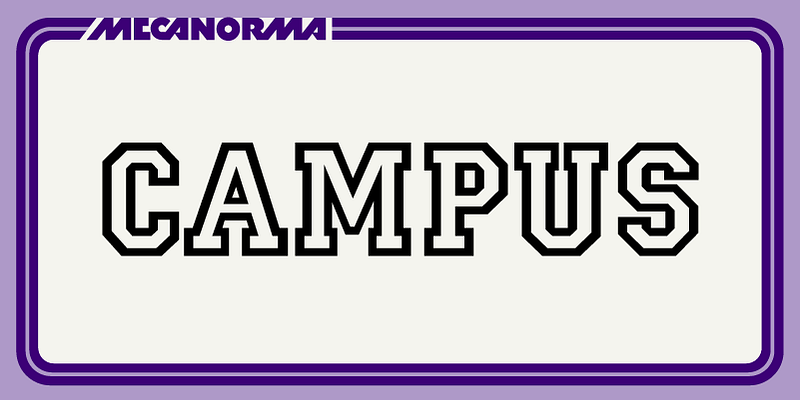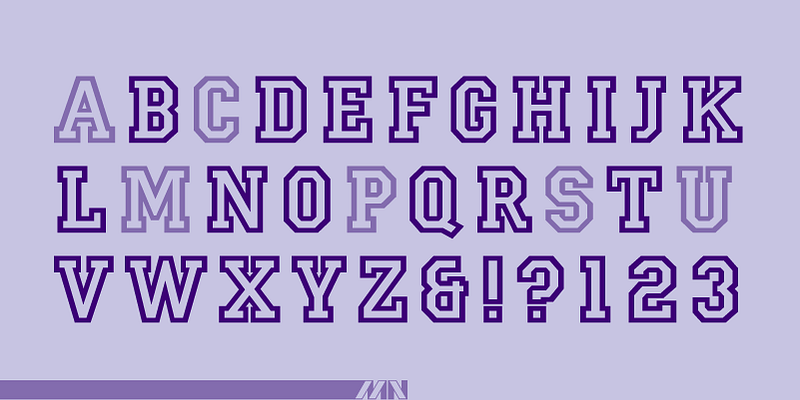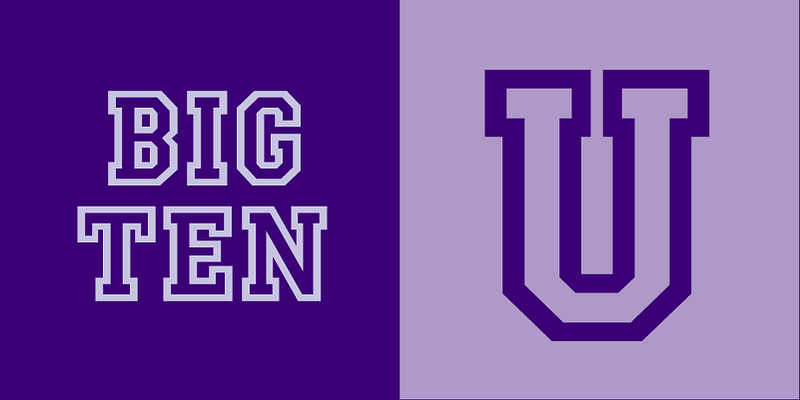
프랑스 기업인 Mecanorma는 인스턴트 럽다운 레터링의 세계적으로 주요한 공급업체 중 하나였습니다. 1995년 Mecanorma는 전문 그래픽 시장에서 물러났습니다. 그 동안 인스턴트 럽다운 레터링 제품은 Trip Productions BV에서 제작했습니다. 2004년 International TypeFounders(ITF)는 Trip Productions BV로부터 디지털 서체를 라이선싱하고 Mecanorma Collection이라는 포트폴리오를 출시했습니다. 이를 통해 오늘날의 도구에 실제 예술과 기술을 결합하여 가장 뛰어난 디스플레이 서체 디지털 글꼴 라이브러리 중 하나를 보존하게 되었습니다. 2014년 ITF는 Trip Production의 후임자와 영구 계약을 체결했습니다. 이 계약을 통해 ITF는 해당 컬렉션에 대한 전 세계적 독점 디지털 권리를 확보하게 되었습니다.